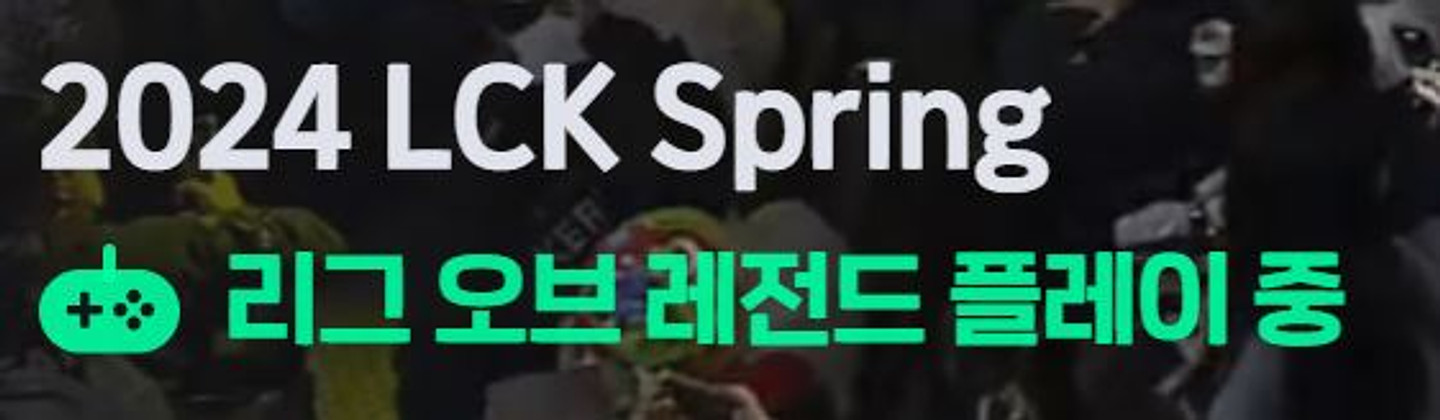
Sandoll 네모니2 (Basic Medium)
산돌 네모니2는 2018년 8월 출시되었던 네모꼴 폰트였습니다. 기존 네모니의 웨이트를 확장한 네모니의 두 번째 폰트이다. Bold 웨이트만 있었던 전작에 비해 Thin, Light, Regular, Heavy 등 4개의 웨이트가 더해졌기 때문에 좀 더다양한 작업에 활용할 수 있게 되었으며, 한글 430자를 추가 제작해 '뀰, 똠'과 같은 글자들도 타이핑이 되었습니다. 그리고 'Ă Ả Ã' 와 같은 글자도 타이핑이 됩니다.
Sandoll 네모니